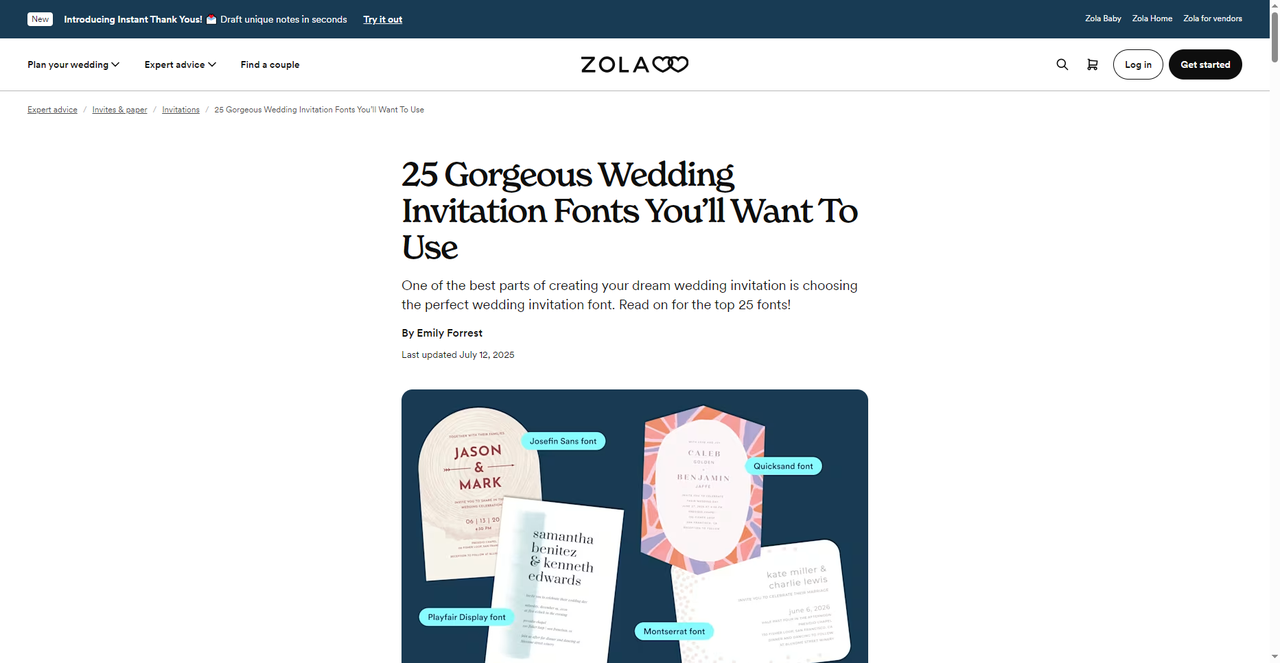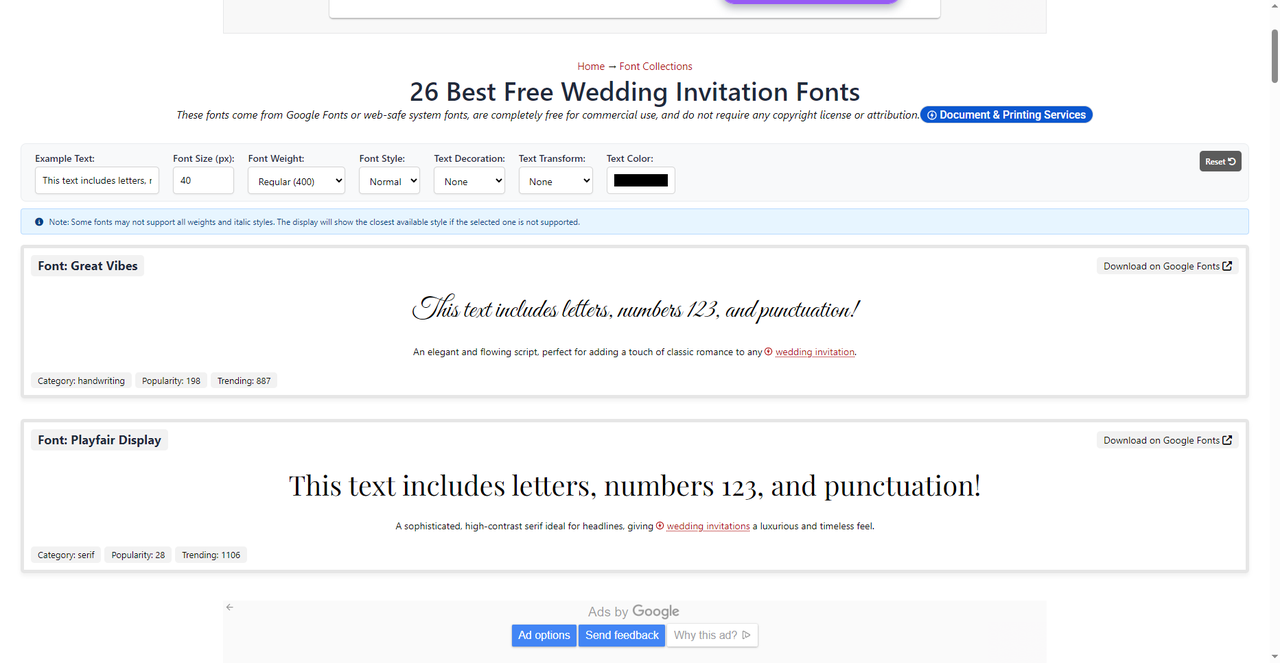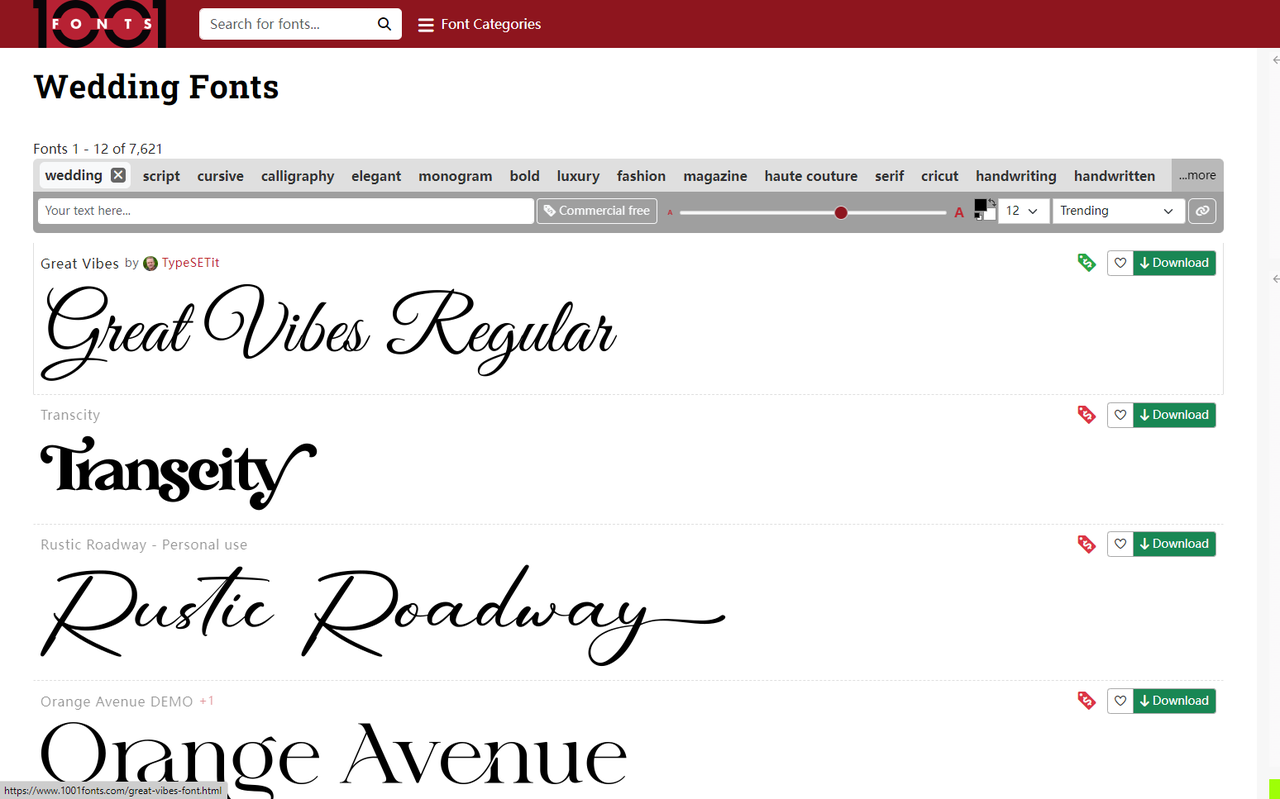
浪漫氛围拉满!5个婚礼请柬字体网站推荐
结婚需要注意的事项确实不少,琐碎的事情也有很多,但其中首先应该纠结的就是请柬。毕竟这是给宾客们的邀请函,字体选对了的话请柬对外表达的效果会直接翻倍,氛围拉满。如果选错了,再贵的纸张也无济于事。很多新人在选婚礼请柬字体的时候,肯定会想着花大价钱请个设计师,但是我想说完全不必。今天在我整理的5 个婚礼请柬字体网站中就能找到你们想要的答案,正在备婚的朋友可以直接收藏,节省时间!
首先我会推荐的婚礼请柬字体工具是字由。字由收录了超过10500款字体,其中包含大量适合婚礼场景的书法体、手写体、艺术体。随便翻翻就能找到:
• 字由芳华体:笔画柔和的手写风格,适合文艺风的请柬
• 江西拙楷:带着朴拙手工感的楷书,适合中式婚礼
• 点字浩蔓:飘逸的手写体,适合浪漫风格
• 点字明刻本婉宋:带有宋体韵味的字体,适合传统风格
2、Minted
这个网站上面有大量独立设计师创作的婚礼请柬,图片中所展示的是此网站自身整理的 25 款绝美婚礼请柬字体,每一款都有精美的示例图展示,那我可以为大家推荐几款我认为不错的字体:
• Agate Portrait:优雅衬线体,适合正式婚礼
• Dermot Photo:带有复古感的字体
• Galena Portrait:现代简约风格
• Jade Multiphoto:清新手写感
• Marvis Portrait、Finnian Portrait、Mabel Photo 等
3、26款Google Fonts精选
这个网站是单独整理出来26 款适合婚礼的免费字体,并且字体源全部来自Google Fonts,完全免费可商用。每款字体都有详细说明和预览:
• Great Vibes:优雅流畅的手写体,为婚礼请柬增添经典浪漫感。分类是手写体,人气很高。
• Playfair Display:精致的高对比度衬线体,适合标题,给请柬带来奢华永恒的感觉。分类是衬线体,也很受欢迎。
4、BRIDES
这个网站是全球知名的婚礼杂志,作为特殊的网站推荐,我选择这个的理由是它里面有一篇是关于如何选择婚礼字体的文章,而且就发布于近期。文章主要给出了下面三个关键建议:
• 字体风格要和婚礼主题匹配(正式场合用脚本字体)
• 确保小字部分清晰易读
• 混搭不同字体制造视觉对比(比如脚本字体配无衬线体)
如果新人们对设计这方面有特殊需求,完全可以看一下这篇文章再进行选择。最重要的是文章还提供了 20 款可免费下载的漂亮字体资源。如果你不确定怎么搭配字体,可以参考专业人士的建议。
5、Wedding Fonts
该网站目前已经收录了超过 7600 款字体,其中婚礼请柬字体也不少。从主页推荐的几款婚礼字体就可以看出,每一款都是精品,都非常适合做请柬。这四款Great Vibes Regular 是经典手写体,十分优雅。Transcity 比较偏向现代感字体,如果作为封面的字体将会很合适。Rustic Roadways 是乡村复古风,但是要注意这个字体仅供个人使用,商用还需付费。Orange Avenue DEMO 仅仅作为展示字体,不过依旧可以作为参考。网站支持按热度、最新、名称排序,也有简单的分类筛选。字体数量够多,几乎能找到任何你想要的风格。